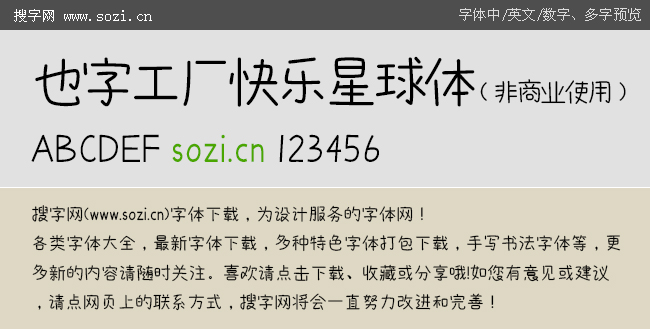
也字工廠快樂星球體
搜字網給大家提供一款也字工廠快樂星球體(非商業使用)中文字體下載,也字工廠快樂星球體是一款卡通字體,字體是可愛的書寫風格,非?蓯塾腥ぃ哂泻芎玫囊曈X效果。適合應用于兒童繪本、兒童海報、網頁設計等應用(此字體為個人非商用版,商用可以聯系:官方網址:https://yefont.com/home,聯系方式:13798980448)。